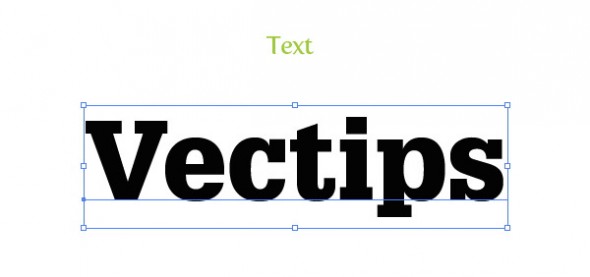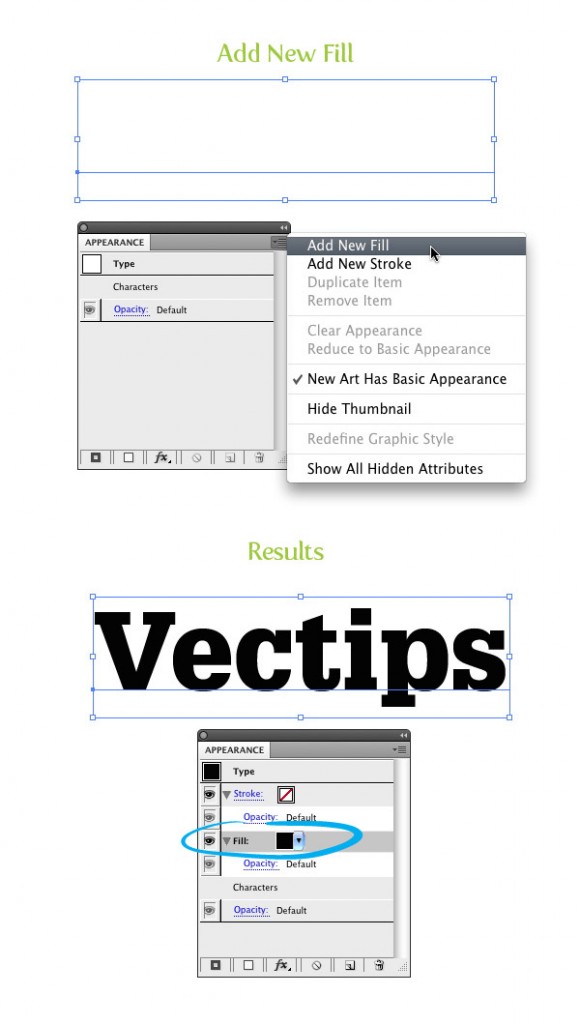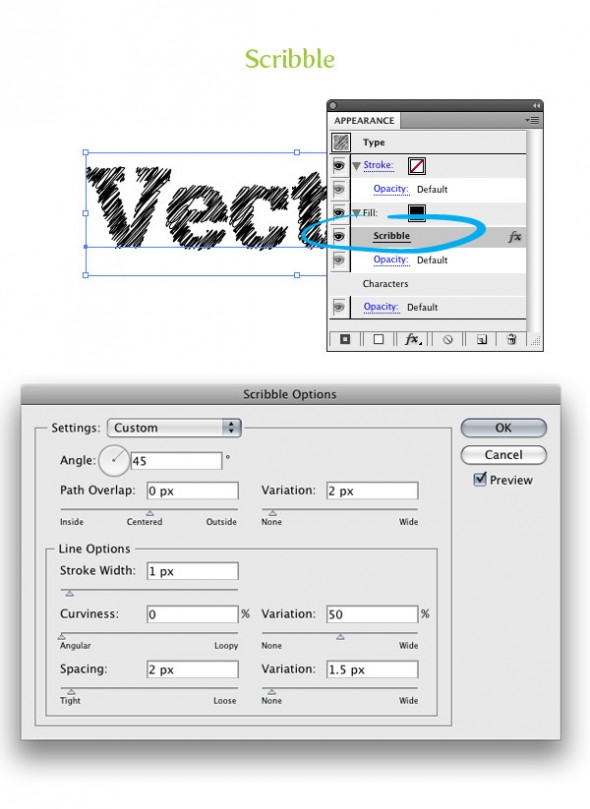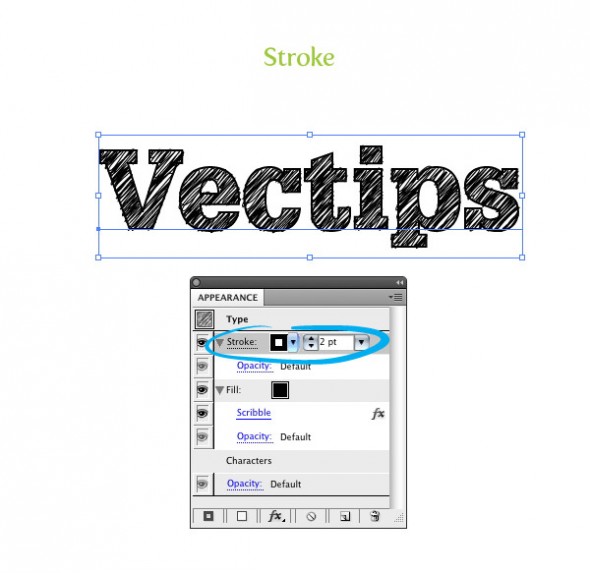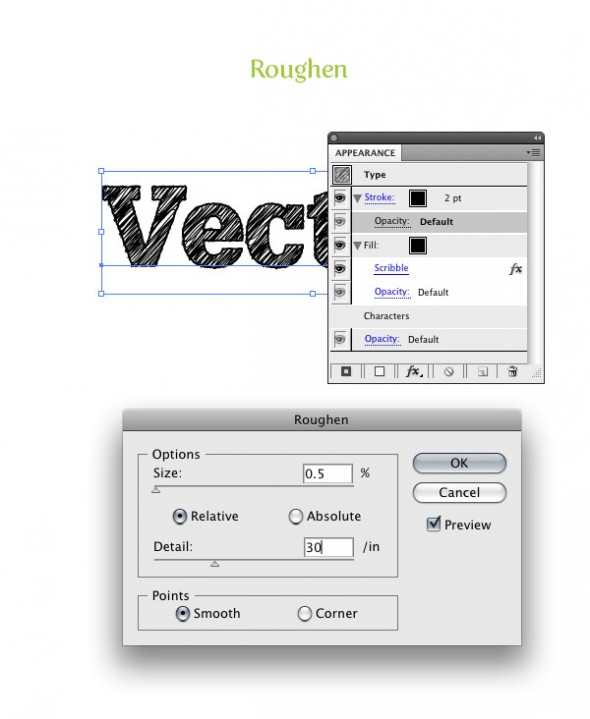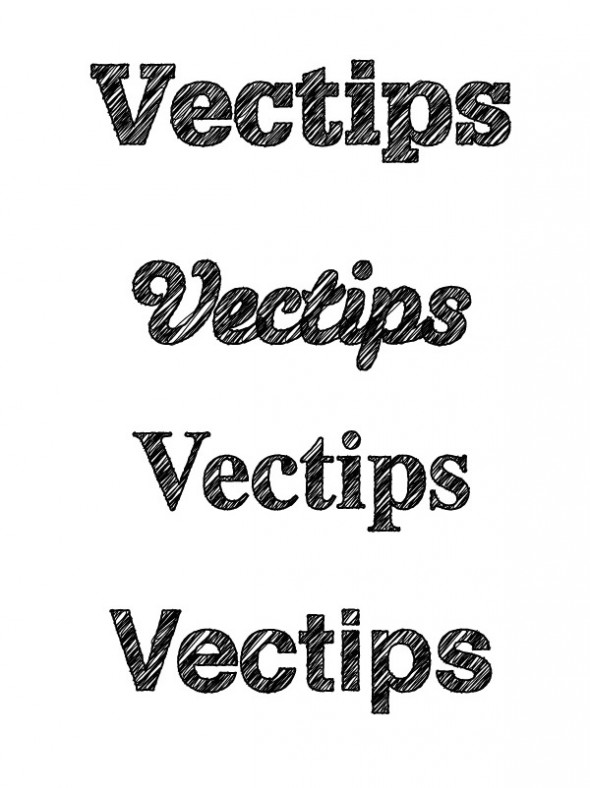
Создаем эффект заштрихованного текста
Сегодня мы научимся просто и быстро создавать эффект заштрихованного текста, нарисованного от руки. В этом уроке много полезного, а главное его достоинство в том, что получившейся эффект можно сохранить и применять к любому другому тексту и графическим объектам.
Результат
Шаг 1
Создайте новый документ и инструментом Text/Текст (T) введите текст, используя любой шрифт. В примере использован шрифт Glypha Black.
Шаг 2
Не снимая выделение с текста, укажите ему отсутствие заливки и обводки. Их мы добавим отдельно при помощи палитры Appearance/Оформление.
Шаг 3
По прежнему не снимайте выделение с текста. Откройте выпадающее меню в палитре Appearance/Оформление и выберите Add New Fill/Добавить новую заливку. Сохраните черный цвет, который выбран по умолчанию.
Шаг 4
Выделите новую заливку в палитре Appearance/Оформление, и в меню выберите Effect > Stylize > Scribble/Эффект>Стилизация>Каракули. Настройте эффект как показано ниже.
Шаг 5
Выделите опцию Stroke/Обводка в палитре Appearance/Оформление и укажите тексту обводку в 2 pt.
Шаг 6
Не снимая выделение с обводки, выберите в меню Effect > Distort & Transform > Roughen/Эффект> Исказить и трансформировать > Огрубление. Настройте эффект как на картинке ниже.
Шаг 7
Теперь у нас есть готовый эффект нарисованного текста. Более того, у нас также есть возможность редактировать текст. Давайте создадим Graphic Style/Стиль графики, чтобы мы могли использовать этот эффект и дальше.
Для начала обратите внимание на палитру Appearance/Оформление. Вы можете видеть все эффекты, примененные к нашему тексту. Теперь просто нажмите на кнопку New Graphic Style/Новый стиль графики и дайте ему имя!
Шаг 8
Теперь вы можете ввести новый текст, используя любой другой шрифт. Не снимая выделение с нового текста, просто нажмите по иконке вашего нового Стиля Графики и смотрите на результат!
Вы также можете применять этот эффект не только к тексту, но и к другим графическим объектам. Также попробуйте поэкспериментировать с параметрами эффектов Scribble/Каракули и Roughen/Огрубление.